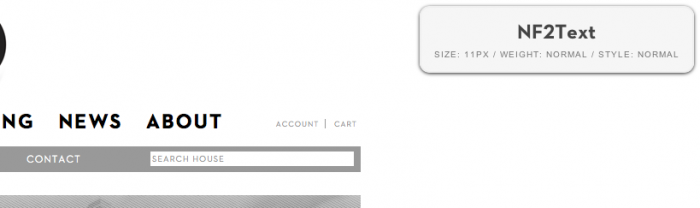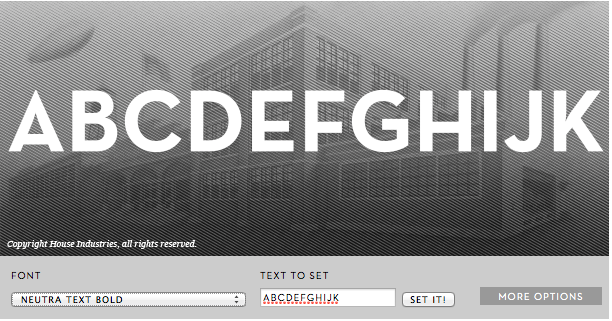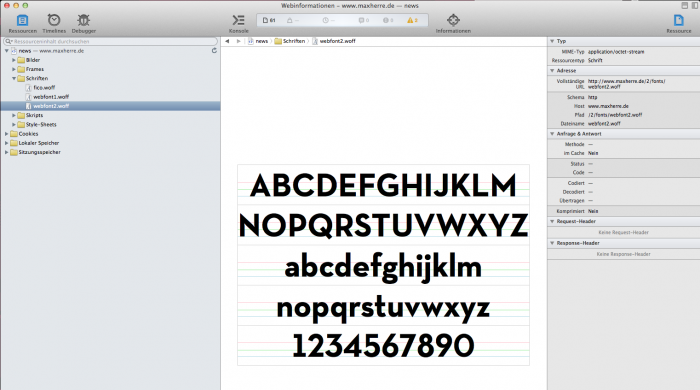
Welche Schrift verwendet diese website?
http://www.maxherre.de
"Fount" sagt mir nur "Webfont2" …
Die Seite selbst bringt mich auch nicht weiter…
Also sie heißt »Richard Herre Bold«. Copyright © 2013 by Rocket & Wink.
Aber es IST eine Neutraface. Wie legal das ist, weiß ich nicht.
Die Mittenhöhen sind aber doch ganz anders … ?
Oder gibt es mittlerweile eine Neutraface2?